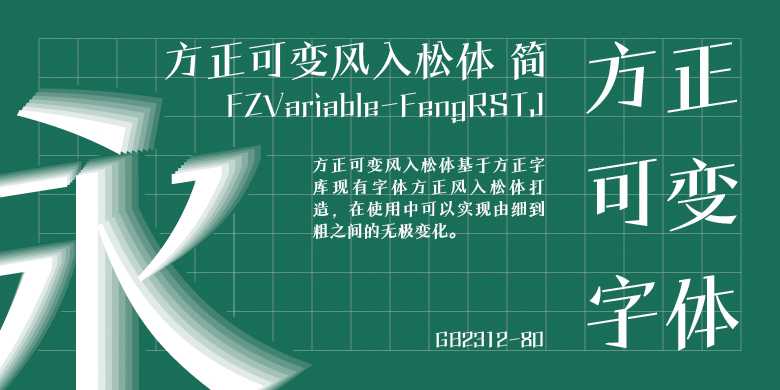
字體名稱: 方正可變風入松
方正可變風入松體 簡
方正可變風入松體字體支持文字粗細無級調節,設計師通過調整字重軸(Weight)的變化,可以實現字形的平滑連續的細微調整,滿足不同版式的設計需求。 風入松體是宋體字的傳承與進化,文字筆畫的銜接和交叉處給人的視覺反應就是堆墨,鏤空的方式本身就很有趣,讓這款字體白區貫通,更加透氣,象風入松一樣高雅靈動,9度的右上傾斜,提振精神,感覺很爽!該字體的應用更側重于標題字,也許能夠起到畫龍點睛的作用。